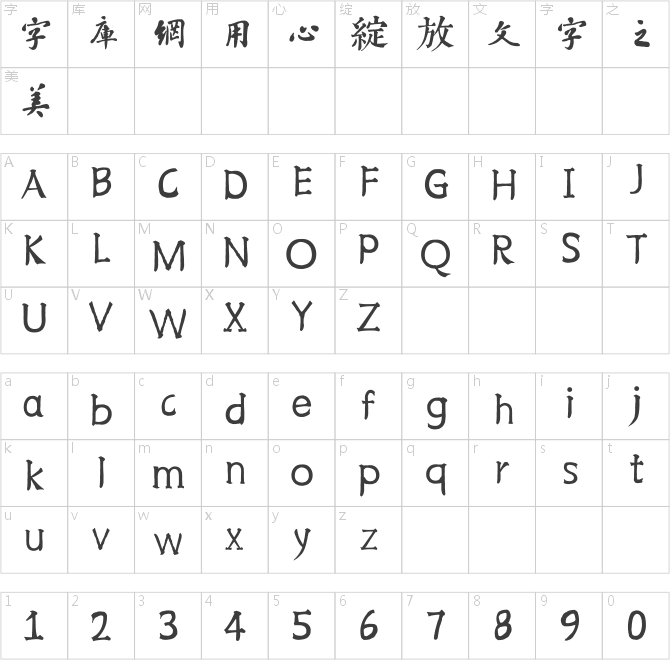
字体名称: 邯郸张謇行书千
邯郸张謇行书千字文
邯郸张謇行书千字文字体下载邯郸(清)张謇行书千字文
张謇[jiǎn](1853年7月1日~1926年8月24日),字季直,号啬庵。祖籍江苏常熟土竹山,生于江苏省海门直隶厅长乐镇(今江苏省南通市海门区常乐镇)。光绪二十年(1894年)状元,中国近代实业家、政治家、教育家、书法家。
邯郸张謇行书千字文字体邯郸(清)张謇行书千字文字库是一款让人赏心悦目、百看不厌的中文字体,适合各类广告和产品包装设计应用,字体大小6.89MB,格式为ttf字体,上传用户是邯郸字库,作者/版权方为韩绍杰